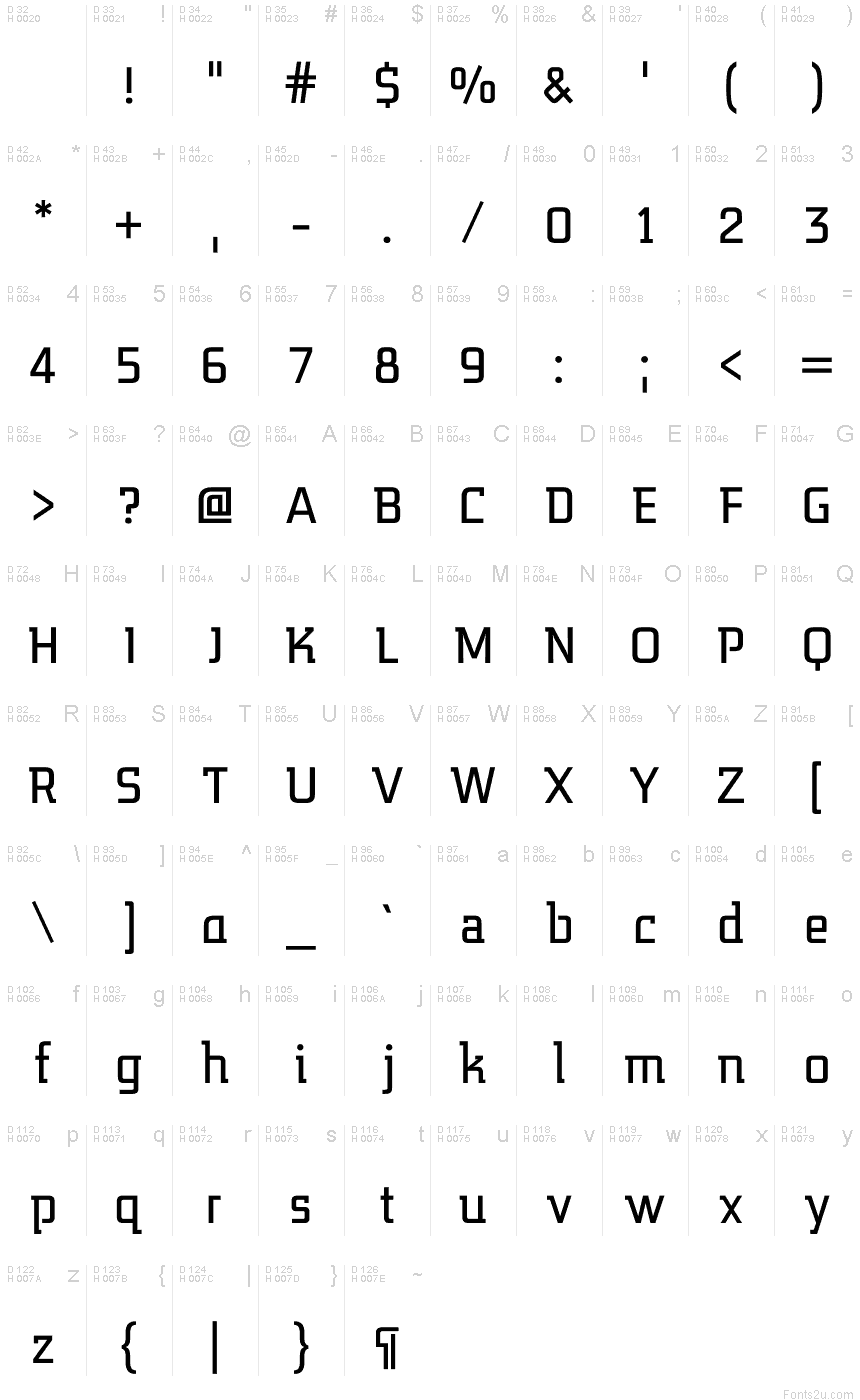
Citizen Kern di James Arboghast di Sentinel Type è un carattere display slab serif gratuito dalla struttura rigorosa e geometrica. Ampie curve rettangolari, serif squadrati e terminazioni dei tratti brusche conferiscono alle lettere un aspetto ingegnerizzato, mentre i punti rotondi ne ammorbidiscono la silhouette severa.
I designer che lavorano nell'ambito della cultura contemporanea, dell'architettura o della tecnologia la troveranno adatta per poster e copertine editoriali. Conferisce inoltre al merchandising musicale e alla grafica per eventi un taglio urbano e deciso, radicato nel contrasto tra forme squadrate e precisi dettagli circolari. Queste forme possono richiamare griglie, illustrazioni modulari o fotografia industriale, permettendo al lettering di diventare parte di un concetto grafico strutturato.